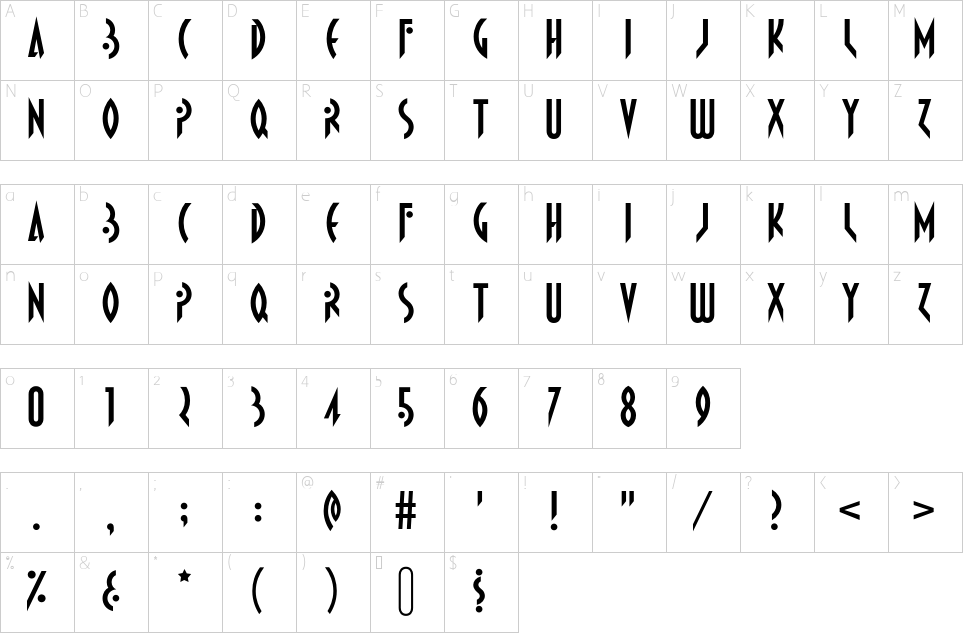
Propaniac é uma fonte moderna e elegante que se destaca em qualquer projeto, seja ele digital ou impresso. Desenhada pela prestigiada Typodermic Fonts, esta fonte é uma excelente escolha para designers e criadores de conteúdo que buscam um visual atraente e versátil. Ela combina facilmente com outras fontes para criar texturas variadas e interessantes. Propaniac foi projetada para atender a uma gama de necessidades, desde textos legíveis e legíveis até design gráfico sofisticado. Se você está procurando uma fonte para seu próximo projeto, Propaniac é uma ótima opção. Com uma versão gratuita e disponível para Windows e Mac, agora é seu momento para experimentar e explorar a sua rica variedade de estilos. Descubra por si mesmo o poder de Propaniac e permita que ela transforme o modo como você expressa suas ideias.